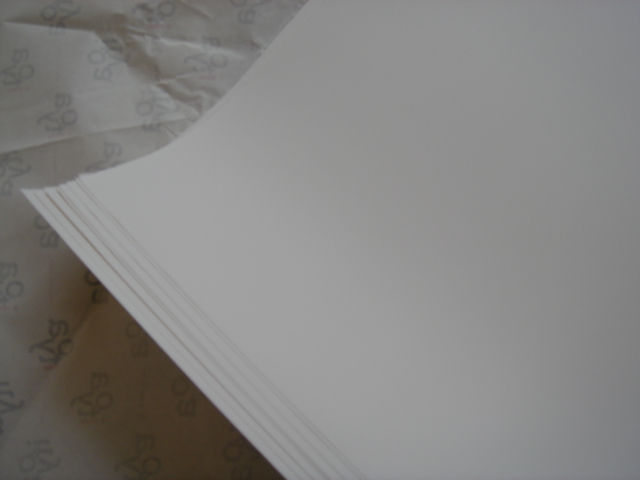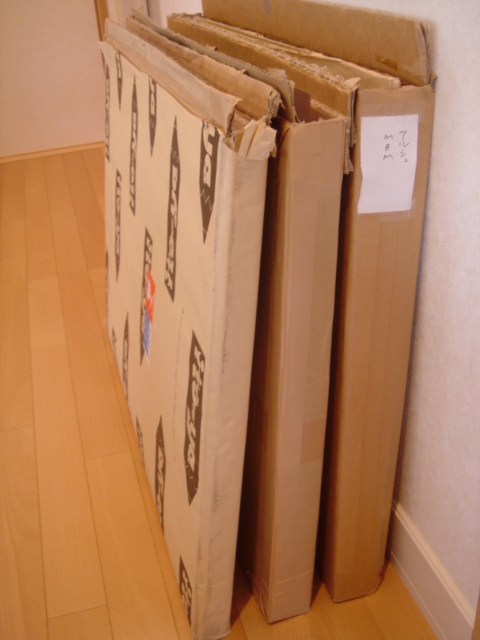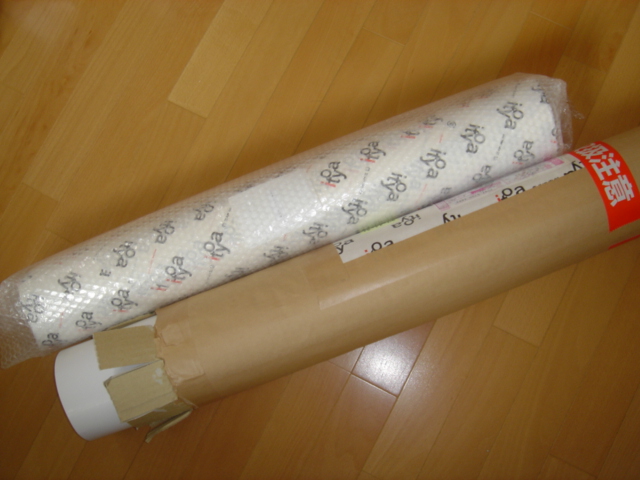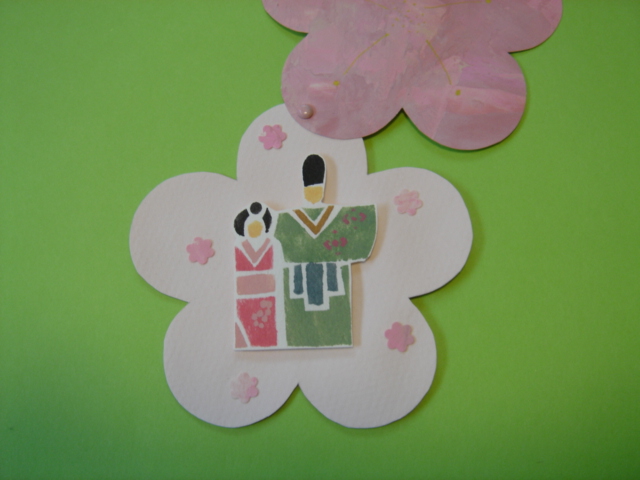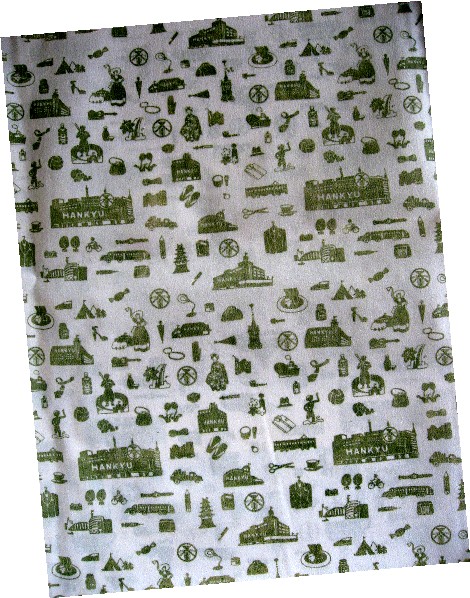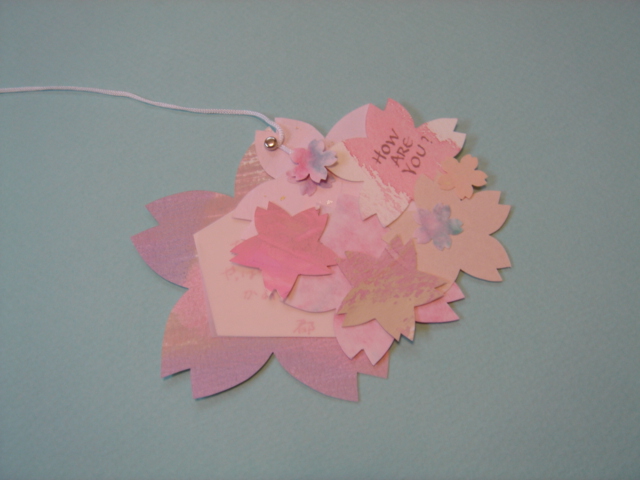
いつも感動していること
今日は画像がダンボール色で地味〜なんですが・・・いつも「すばらしい!」と感動していることなのでちょっと書きたくなりました。
紙を画材屋さんに買いにいくのはとっても楽しいことなのですが、なかなか出かけられないときには注文して送ってもらうことがあります。
買いたい紙が決まっているときはいい方法ですよね。
時々お願いするのは銀座の伊東屋。
いつもいつも感激してしまうほどの、丁寧な梱包です。今回は丸めて送ってもらったのでこんな感じ。
包装紙に包んだものをプチプチでくるんで、厚紙で巻いたものが、更にダンボール状の梱包材で巻かれています。
メルシー券もきちんと貼り付けてあって、うれしい!
包みを開けると、ひとつの傷も汚れもない美しい状態で紙が現れます。このことに私は毎回感動しているのです。
もちろん、たいていのお店ではきれいに包んでもらえます。でも、ごくごくたま〜に、紙の扱い方が「・・・(泣)」な人にあたってしまうことがありました。通販で買った紙もときどき「あらら・・・なぜ?」と思うことがあります。
伊東屋さんは品揃えも日本一だと思いますが、やっぱりこの商品に対する丁寧さに愛情が感じられて「大好き」なお店です。
お願いすると平たい状態で送ってもらうこともできます。(梱包料、送料が普通のより高いです)この平たい梱包も完璧なんですよ!
紙は種類別に包装紙で包まれて、分厚いボール紙にのせてからプチプチでくるまれています。
間にもきちんとボール紙が入っているし、外側のダンボールもぴったりサイズに作ってあります。本当に手間がかかっています。
以前のこのダンボールもとってありまして、私はそのまま紙の保存ケースとして使っています。大きいマップケースを買いたいけれど置く場所がないので・・・(お金もないけど)
紙が充分にあると本当に幸せな気分。今回もやっぱり伊東屋さんに注文してよかった、満足満足、でした。あとは書くだけだ!
春の下地つくり
春なので水彩絵の具で作った下地の紙を使って何か作ろうかと思います。クラスで下地を作るテクニックを説明した時に出来た紙をゴソゴソ出してきました。
水彩絵の具にはいろいろな下地を作るテクニックがあって、それぞれが違った表情を作り出せるのでそれはそれはとても楽しいのです。
上の左は、ご存知ウェットな時にお塩をパラパラのテクニック。よく粗塩とか岩塩とか聞きますが、私が思うに普通の食卓塩がパラパラときれいに撒く事ができるので一番!あまり水が多いとお塩は溶けてしまうだけなので注意!乾きすぎてもだめですけどね。
右はローラーです。びしょびしょな絵の具でローラーして乾いた上にドライにした(他の紙でかなり絵の具を取ってから)ローラーで色をつけました。ローラーはスポンジの柔らかなものです。
ふふふ、これは一体なんでしょう。SLUGみたい〜!なめくじ!
なんだかオレゴンの巨大なSlugを思い出しました。すっご〜くデカくてしかもカラフル。雨が良く降る秋から春にかけて、出没しました。
このSlugは実はアルコールでできたもの。濡れているあいだにアルコール(エタノール)を筆に付けてさっと塗りました。すると絵の具をぱっとはじいてこんな感じになるのです。
さぁ、みなさんも可愛い春色のSlugちゃんを作ってみて下さいね。
水彩絵の具でイメージ通りの下地を作るのは至難の業ですが、気楽に作ると思いがけない素敵なものが出来るかも。
3月のエクスチェンジカード
3月のエクスチェンジカード、,最終回です!
春、春、春! プリマベーラ!
3月のカードとして春らしくやさしい二つのカードが届きました。
カワイイ〜!!
ウレシ〜!!
お花はよく見ると小さなスタンプを押してある様です。きっと作ったのでしょう!なんという手の込んだカードなのでしょう。本当に手作りの良さが表れている素晴らしいカードですね!
さてもう1点はKIさんからのカードです。こちらもWonderfulです!
パステル、エンボスを使った柔らかなイメージのカード。
きみどり色のクロマティコとピンクが春そのものの色で素敵です。
中を開いたら!
こちらは色鉛筆で描いてあります。もうやられた!と言う感じです。
あまりにも可愛いのでアップをどうぞ!
このカードの素敵なところは、紙や色の選択、きちんと書いた文字、エンボスやパステルなどのいろいろなテクニック、といろいろありますが、光っているのはこのとても素敵な文章です。
Listen, can you hear it?
Spring cantata....
The tender timpani of baby robin's heart......
D.Frolov
このひよこちゃんは、こまどりの赤ちゃんだったんですね〜
3月で最後となったエクスチェンジカード。いろいろなアイデアをご紹介できて本当に楽しかったです。私の手元には素敵なたくさんのカードが集まりました。大事に致します!
モジトルではまたこういう企画をして参りたいと思います。
エクスチェンジカードに参加されたみなさま〜、おつかれさま! またよろしくお願い致します!
芸術はどこで創られる
ダ・ヴィンチ展が始まっています。上野はこれから春爛漫、きっとすごい人出になっていることでしょう。
「受胎告知」ももちろん見たいし、素描をもとにした模型(科学系のほう)もたくさん出ているそうなので楽しみにしています。
朝日新聞社も主催になっているから記事が連日出ていて、行きたい気分が盛り上がってきます。
(東京国立博物館で6月17日まで)
そうだ、行く前に、もう一回読んでみよう、と棚から出したのがこの本。レオナルド・ダ・ヴィンチについても書かれていて、「モナ・リザ」、「最後の晩餐」「岩窟の聖母」などがとりあげられています。
イメージを読む
イメージを読む―美術史入門
すでに文庫が出ているのですね。
美術史入門とありますが通史ではありません。
とっつきやすいです。それは、美術についての知識がない人に向かって、講義のように、一緒に絵を見ながら語りかける形で書かれているから。図版も豊富で(カラーでないのが残念)、はじめて読んだときは一気読みしてしまって、かなり興奮しました。
一瞬わかったつもりになってしまう・・・のがコワイです。やっぱり、簡単にわかろうとするなんてずうずうしいのです。こういう学問がある、ということに尊敬のまなざしをおくってしまいます。
今回展示されている「受胎告知」はレオナルドが独立した頃の作品ということです。
ということは、その前は独立していなかった・・・つまり先生についていた、わけなのですね。
この本を読んで、レオナルドが弟子入りしていた「工房」の説明のところがとても印象的でした。
以前は私は勝手なイメージで先生と弟子の1対1の関係を思い描いていたのですが、そうではなくて
かなり大きな(しかも有名な)工房に先生とたくさんの弟子がいたそうです。そこで、技術が伝えられ、芸術作品が制作されていた、と。
そういわれてみれば、中世といえば職人!の世界。弟子は親方や兄弟子から芸を盗んで大きくなっていったのかな。新入りさんは最初はお掃除とかから始まったのかしら?若い芸術家のタマゴたちがイキイキと動く姿を想像してしまいます。
のちにレオナルドは先生の作品の端っこに絵を描かせてもらえるようになって、先生はその絵を見て筆を折ってしまった、とのこと。工房では涙と汗と、そして嫉妬も渦巻いていたかもね!
京都の道具
京都、清水寺の3年坂でこんなお店を発見。筆屋さんかと思って入ったら、陶芸の店でした。茶道用のお茶碗専門の店です。嘉祥窯
中では陶芸教室もやっていました。おみやげやさんのらく焼きではなく、もう少し本格的で、 焼き上がりの色(釉薬)は選ぶ事が出来るようでした。今は季節の色で桜色がきれい。
柄の部分を見ると、尖っているのもあります。きっとこれで模様を付けるのかもしれませんね。
竹の柄にちょこっと差し込まれて付いているだけなので、長くはもたないかもしれませんが、どんな線や文字が書けるでしょう。かなり柔らかくコシがないので、リスの毛の筆と同じ様な太くてぽってりした線になるかも。
次回は伝統工芸の道具ばかり探しに行く旅がいいかも〜!
2007年03月26日
阪急さんの風呂敷
また、実家で発見しました…母よ…貴方は何でもしまい込んで
あるのですねぇ〜。
でもこれは結構使用した感じです。
一体いつの頃のものなのでしょう…。
私の存在しない頃は関西にも居住していたようですが、
母の青春は入っているのかな?
しかし、キュートな柄です。一目見て気に入りました。
これはデパートの建物とロゴが入っている風呂敷で、
阪急デパートのもののようです。
よく見ると、デパートの建物もいくつかあるようですねぇ…。
支店なのかしら?
HANKYUのロゴも今とは違うの
でしょうか…?
関東者なのであまりよくわかりません…。
いろんな物たちがてんこ盛りで
デザインしてありますねぇ〜。
しかも素朴な感じが可愛いです。
何でこんなに長〜〜いバスがいるのでしょう?
隣にはえんぴつ?時計、何で注射器?
お城までありますよ〜。
何だ、何だ…いったい何事だ?
きっともっとデパートでのお買い物がステータスだった頃の
色んな売っているものとか、関西の有名なものとかが
デザインされているのでしょうかしら〜?
どんなお買い物をして、この風呂敷で包んでくれたのでしょうかねぇ…。
子供の頃はデパートに行く母にくっつき虫して、お利巧にしていると、食堂でお子様ランチとか
パフェとか食べさせてもらえました…。楽しい思い出ですね。
今は過剰包装を無くす傾向ですから、こんなオリジナル性のあるものは記憶の中だけの
産物になるのかもしれません。
2007年03月25日
カードエクスチェンジ番外編 こっちも!
今月で終了したモジトルカードエクスチェンジは二つのグループに分かれていまして
私はBグループの発送担当でした。この10ヵ月間、参加者のみなさまからご覧のような季節感あふれるカードや流麗な文字(みなさん本当に字がお上手なんです)でのお手紙をいただきました。体調を気遣ってくださったり、励ましてくださったりで、毎回とても楽しくうれしく拝見していました。
この場をかりてお礼を申し上げます。ペーストペーパーのカード、夏らしい色が美しいですね。
デザインに凝ってたんですねぇ〜。ステキでしょう〜!
よく見るとほら!お魚の下に「stig.L.」ってサインがあります。
リンドベリのサインっていろいろあるらしいのですが、どれも
キュートなんですよねぇ…。
包装紙に所狭しと並んでいるものたちは切り絵なんでしょうか?
手作り感があって温かみがあります。
こんな古い包装紙を残してくれている母よ、貴方は偉い!
この本の中にも西武の包装紙デザインが載っています。
1959年のデザインでは、西武のマークはもっと小さくてロゴも「seibu」
と小文字。丸みを帯びている小文字がデザインとマッチしていて可愛い
です。
画像の包装紙は改訂版?なのでしょうか…。ロゴが「SEIBU」と大文字に
なっていて漢字の西武も入っています。年代がはっきりしません。
そして謎なのが、魚とワインの瓶?の間の余白です。1959年のデザインにはその間にこけしのようなお人形の絵がありました。他にも猫の顔がありました。
しかし、家にあった包装紙には無くそこが空白になっているのです。
う〜ぅん…ミステリーです。どんなストーリーがあったのでしょうねぇ…。
どなたか事情通の方〜教えてくださ〜い!